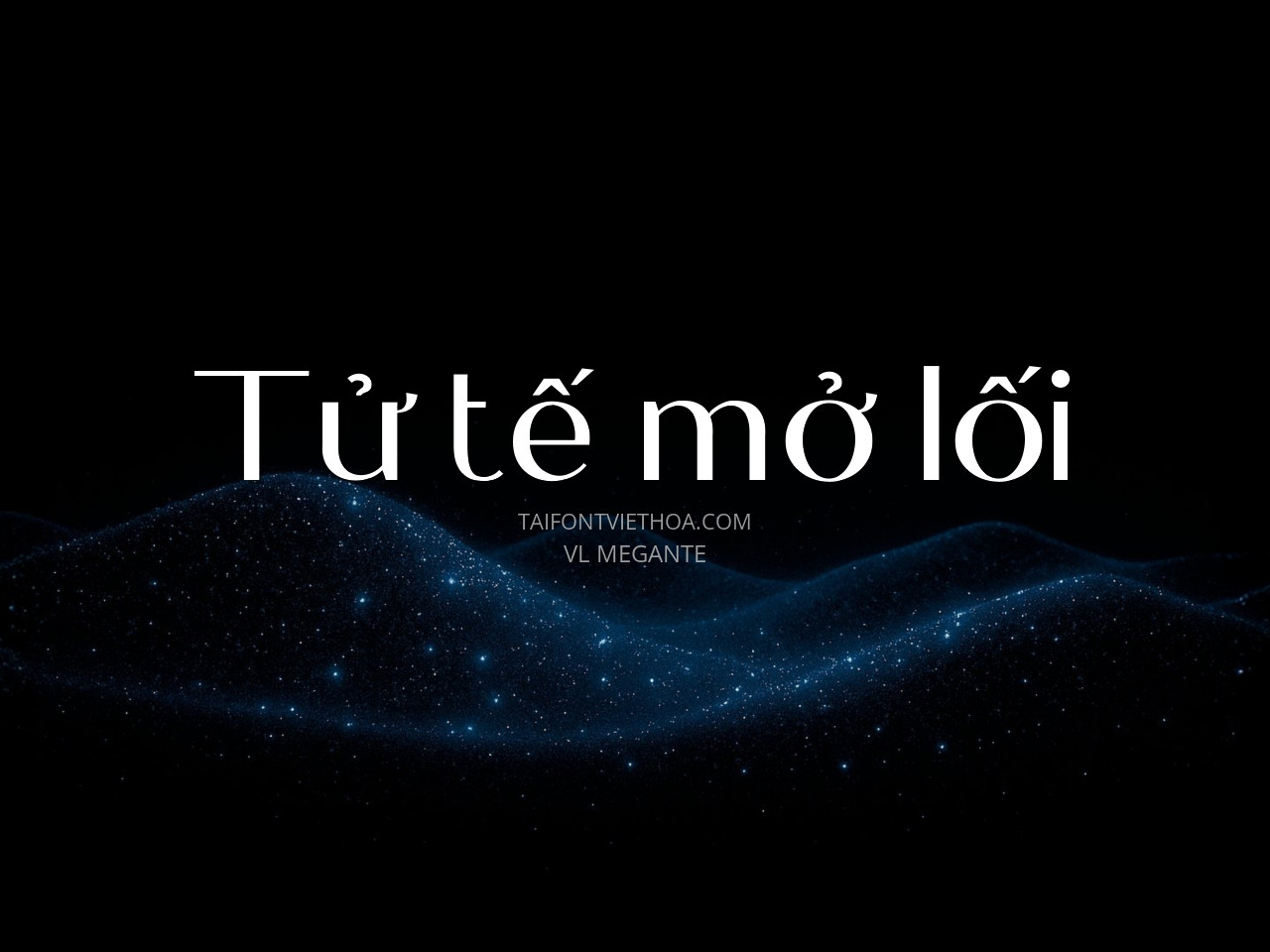
Font việt hóa VL Megante
Giới thiệu về font VL Megante
VL Megante là một font serif hiện đại mang hơi hướng cổ điển pha trộn sự thanh lịch và mạnh mẽ. Font có tỷ lệ cân đối, phần chân chữ rõ nét với các đường cong được xử lý mượt mà, rất phù hợp cho những dự án cần sự sang trọng, tin cậy và đậm chất thương hiệu. Phiên bản Việt hóa được thực hiện bởi Font Việt Linh, hỗ trợ đầy đủ tiếng Việt với hệ dấu chính xác và sắc nét. Ngoài tiếng Việt, VL Megante còn tương thích với hơn 60 ngôn ngữ khác nhờ bảng mã Latin mở rộng. Font này đã được taifontviethoa.com sưu tầm, chọn lọc và áp dụng hiệu quả trong các dự án thiết kế cao cấp như branding, truyền thông và xuất bản.
Đặc điểm thiết kế và ứng dụng của VL Megante
Font sở hữu cấu trúc serif truyền thống với độ tương phản cao giữa nét dày và nét mảnh, kết hợp với các chi tiết hiện đại giúp tăng tính nhận diện. VL Megante có thể ứng dụng linh hoạt trong cả in ấn và thiết kế số, từ tiêu đề cho đến văn bản nội dung. Đây là lựa chọn lý tưởng cho các dự án thương hiệu cao cấp, tài liệu biên tập, hay thiết kế poster sang trọng.
VL Megante phù hợp với thiết kế tạp chí, sách nghệ thuật, ấn phẩm quảng bá thương hiệu, bao bì mỹ phẩm, logo thời trang, danh thiếp, và website cao cấp. Ngành nghề ứng dụng gồm: xuất bản, thời trang, bất động sản cao cấp, giáo dục, mỹ phẩm và truyền thông thương hiệu.